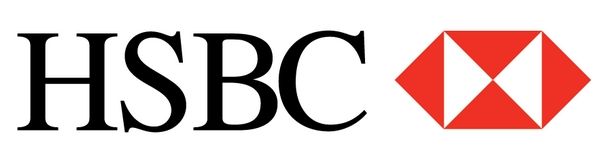
世界名牌是怎样选用字体的?知名品牌选择字体的方法
名牌之所以成为名牌,常常是由于企业的决策者能注意到诸多常人无心关注的细节。
比如,字体。选择合适的 Logo 字体,可以在最直接的视觉观感上传递品牌的信息,其重要程度不亚于文字本身。
所以,世界级品牌对于字体选择的严苛程度,往往是小企业无法想象的。下面我们一起来看看福布斯榜上的各大名牌企业都选用了什么字体,并观察一下其中的规律与趋势。
人人都爱 Helvetica
相信没有人会对 Helvetica 的流行产生异议吧。在平面设计中,Helvetica 的通用性和普适性使其倍受喜爱,这种简洁、端正、优雅的字体,永远都是不会出错的选择。
于是,选用 Helvetica 的品牌跨越了各种行业:丰田、塔基特百货、宝马,通用汽车,美国服饰……
有些大公司虽然没有直接使用 Helvetica,但仍选择了与 Helvetica 相近的 Arial 和 Univers,不过一般用作二级字体。
Helvetica 在上世纪 50 年代就被认为是一种新颖而时尚的字体,而能长盛不衰地一直沿用至今,从一个侧面说明了它的美是经得起时间考验的,而从另一个侧面也能说明,它的广泛使用已经不能给品牌带来足够强的辨识度。
科技与金融的「人性化」风格
许多科技公司的 Logo 都是比较简约的,而对自己网站上的文本则通常会选用一种更加轻松欢快的字体。有些乍一看是 Helvetica,但细细看来,笔画的宽度、尾部的形状,角度,都有显著的区别。
其中最著名的当然是 Myriad,苹果、沃尔玛、领英、Mashable 等公司都在使用。其余和 Helvetica 相关的字体还有 Segoe(微软)、Open Sans(谷歌)和 Lucida Grande(Facebook)等。
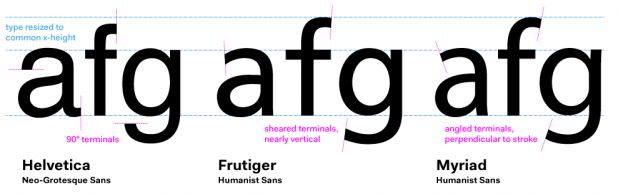
沃尔玛的设计风格指导书中是这样谈字体选择的:
我们选择了一个能使沃尔玛看起来友好、温馨、真诚的字体:Myriad Pro。Myriad Pro 是一个人性化的无衬线字体,能给人带来亲切、简洁的阅读体验,能够拉近我们与用户之间的距离。相较于其他字体,Myriad Pro 更适合沃尔玛的品牌。
奢侈品牌和银行多用衬线字体
奢侈品厂商主要依赖实体店的销售,相对于注重网络营销的企业来说,衬线字体是更常见的选择。非衬线字体在屏幕上的视觉效果比较好,而衬线字体在印刷品上看起来更加优雅,易读性更强。
于是,奢侈品牌通常用衬线字体来体现其高贵血统,而一些银行则通过衬线字体来体现他们的悠久历史以及对客户的信誉。
定制专用字体
还有一些世界顶级企业选择为自己的品牌特别定制一套字体,以彰显其与众不同的特质,提供一种全新的视觉体验,同时把品牌的定位提升到另一个高度。
Intel 最近揭晓了其史上第一款专用字体——Neo Sans Intel。据 Design Week 称,英特尔计划「(把这套字体)应用于所有文字系统、媒体和设备上,作为其品牌的外延」。
显然,重新设计字体,明显要比获得现有字体授权的成本要高得多,不论时间还是金钱。所以,定制专用字体,需要建立在现有字体无法满足当前品牌定位与需求的基础上。
除 Intel 外,还有两家使用专用字体的公司:三星(Samsung InterFace)和通用电气(GE Inspira)。
不一样就不一样
尽管无衬线字体得到了越来越多的青睐,但仍有几家名牌企业没有选择跟随。Google 可能是目前世界上唯一仍在使用衬线字体(Catull)的互联网公司了。
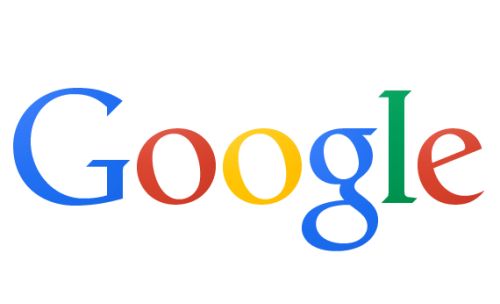
在 Helvetica 阵营中,给 Logo 选用连体字可以马上使视觉观感与众不同。比如,可口可乐和百威。
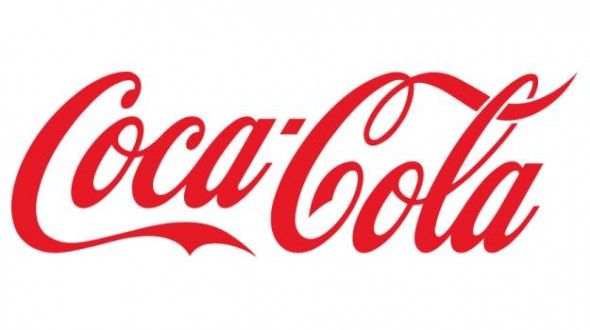
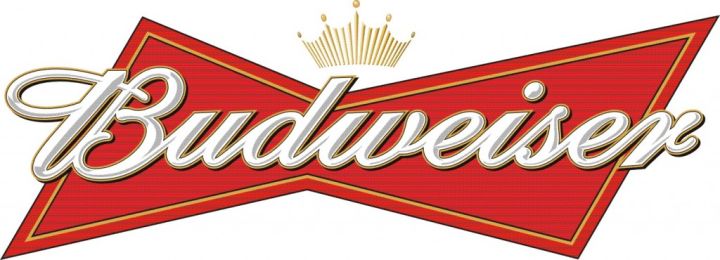
最后的话
字体,与文字本身是不可分割的整体。它能在潜移默化间左右着你的阅读体验,甚至决定了你对文字内容的情感趋向。
字体的选择,和字体的设计一样,都是一门艺术,更是一种技术。在为 Logo 选用字体之前,应确认自己的品牌将向世人传递一种怎样的价值观、情感以及美感,并向字体设计方面的专家进行咨询。